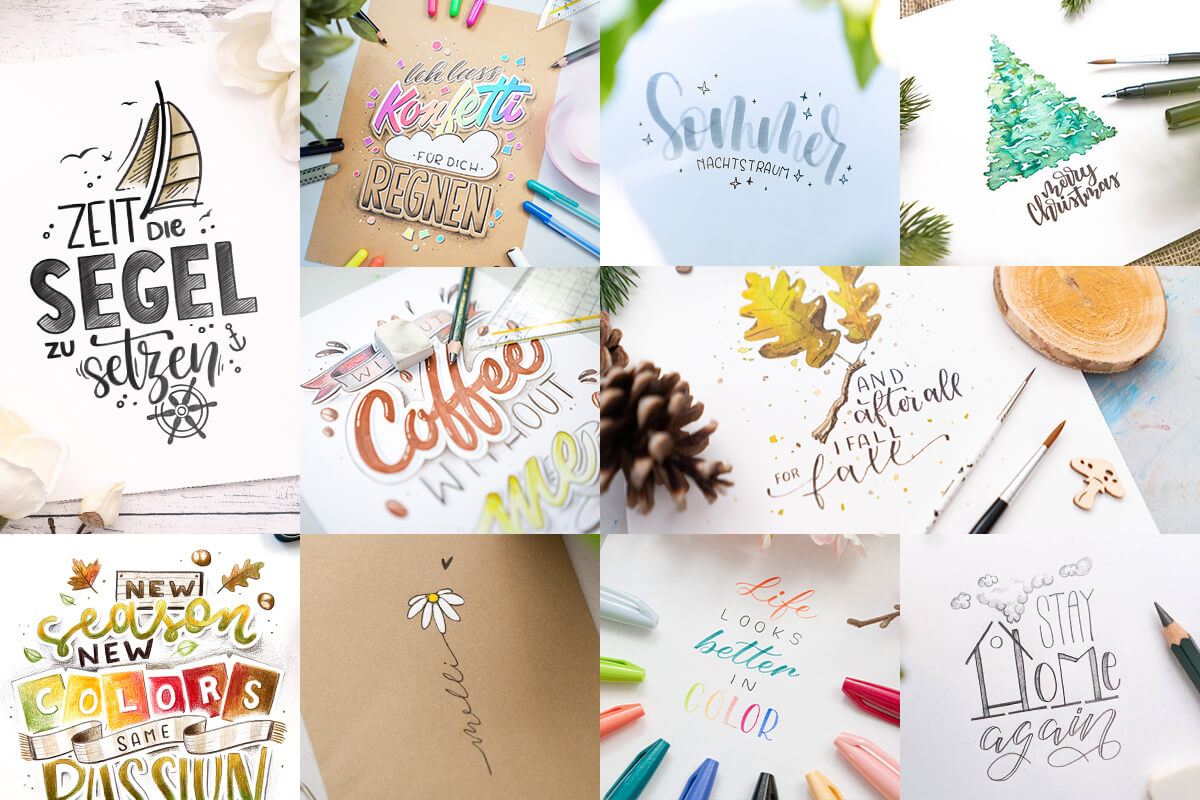
Ahoi! Du möchtest also Handlettering lernen. Die Kunst, Buchstaben, Wörter und Texte besonders schön zu schreiben. Eine gute Entscheidung!
Es ist kreativ, beruhigend, künstlerisch und sieht einfach großartig aus. Gleichzeitig macht es Riesenspaß.
Ich zeige dir hier Schritt für Schritt, wie du das Handlettering lernen kannst und möglichst schnell erste, eigene Schriftzüge zauberst. Dich erwartet hier keine graue Theorie oder Kalligrafie-Geschichte. Hier wird gemacht!
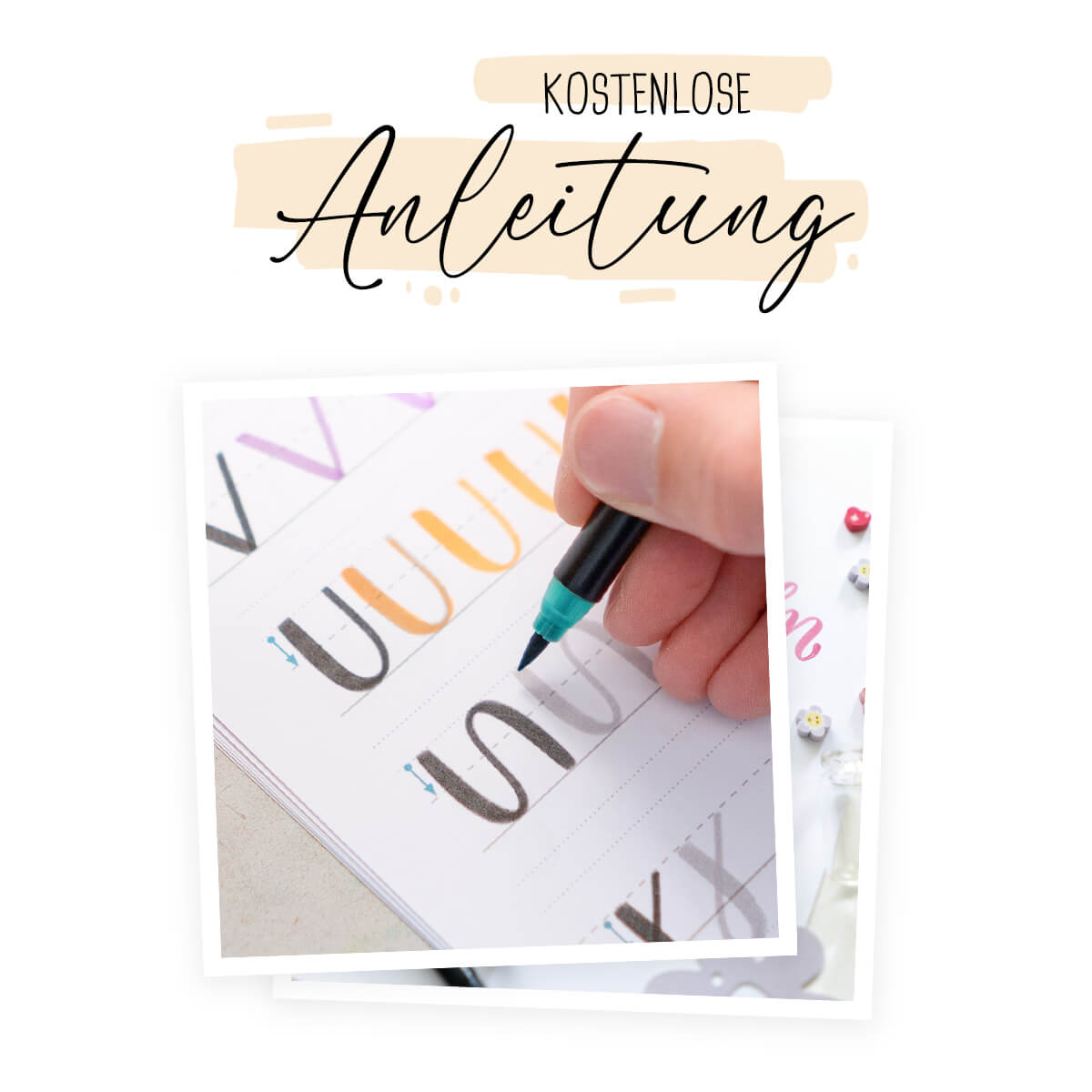
Grundlagen, Materialtipps und einen Einblick in verschiedene Techniken bekommst du direkt auf dieser Seite.
Kurz zu mir, damit du weißt, wer hier schreibt: Mein Name ist Timo (bekannt als Timo Ostrich) und ich bin begeisterter Handlettering-Künstler, Autor und Designer.
Ich habe seit über acht Jahren groooßen Spaß am Lettering und möchte bei dir dieselbe Begeisterung entfachen! 🙂
Du sollst durch die Hilfe meiner Webseite möglichst früh einfache Letterings erstellen und erste Erfolge feiern.
Dazu findest du hier einfache Vorlagen und Übungsblätter zum selbst ausdrucken. Und natürlich eine riesige Anleitung, die über die letzten Jahre immer weiter gewachsen ist und alles Wichtige enthält, was du zum Handlettering lernen wissen musst!
Und jetzt, ganz nach den Worten „Fange zu tun an, dann hast du auch die Kraft dazu“, von Ralph Waldo Emerson, fangen wir an. Los gehts!
Das richtige Material für das Handlettering
Für das Handlettering brauchst du natürlich passende Stifte und etwas Papier. Im einfachsten Fall startest du mit einem normalen Bleistift.
Für besondere Schriften brauchst du manchmal auch spezielle Stifte. Welche das genau sind, erfährst du in dieser Anleitung.
Ich sage zwar immer, das Werkzeug macht nicht den Handwerker, aber gerade beim Handlettering ist eine gewisse Grundausstattung sehr hilfreich!
Du hast natürlich die Möglichkeit mit dem zu starten, was du zu Hause hast. Ein paar Stifte und etwas Papier wirst du sicher haben.
Damit kannst du bereits sehr viel mehr anstellen, als du vermuten würdest!
Die richtigen Stifte
Stifte mit einer flexiblen Spitze haben den großen Vorteil, dass sie „Druck-Sensitiv“ sind. Das bedeutet, je doller du aufdrückst, desto dicker wird der Strich. Genau wie bei einem Pinsel (englisch „Brush“).
Für den Anfang solltest du dir also einen solchen Pinsel-Stift (Brush-Pen) zulegen. Das ist eine Kombination aus Pinselspitze und Filzstift.
Damit kannst du schreiben wie mit einem hochwertigen Pinsel, brauchst aber nicht ständig absetzen um neue Farbe aufzunehmen. Auch ist der Farbfluss immer gleich stark. Der perfekte Kompromiss!
Mit einem Pinsel-Stift für Einsteiger wirst du schnell deine ersten Erfolge erzielen! Das geht allerdings nicht ohne regelmäßiges Üben.
Die Pinsel-Stifte sind übrigens der Grund, warum dieser Bereich des Handletterings auch Brushlettering genannt wird. Irgendwie logisch, oder? 🙂
Welche Brushpens eignen sich für Anfänger?
- Die Pinselspitze ist flexibel, aber nicht zu weich
- Die Stifte sind robuster als andere Brushpens
- Du hast direkt mehrere Farben zur Verfügung
- Die Spitze lässt sich umdrehen, sodass du die Lebensdauer deiner ersten Brushpens verdoppeln kannst
Damit sind sie perfekt zum Üben, Lernen und Ausprobieren. Sie verzeihen auch den ein oder anderen „Fehler“ in der Handhabung. Die Brushpens zählen zu den „mittelgroßen“ bis „großen“ Brush Pens.
Natürlich gibt es auch andere, tolle Einsteigerstifte! Ich gebe hier lediglich meine Meinung und Erfahrung wieder.
Um das Hand- und Brushlettering mit den Edding Brush Pens zu lernen, habe ich dir einen Brushlettering-Guide erstellt, welcher perfekt auf diese mittelgroßen Stifte zugeschnitten ist.
Die besten kleinen Brushpens
Die meiner Meinung nach besten Brushpens mit einer kleinen Spitze sind die Pentel Brush Sign Pens. Sie sind sehr gut zu beherrschen, relativ robust und können dich viele Jahre begleiten.